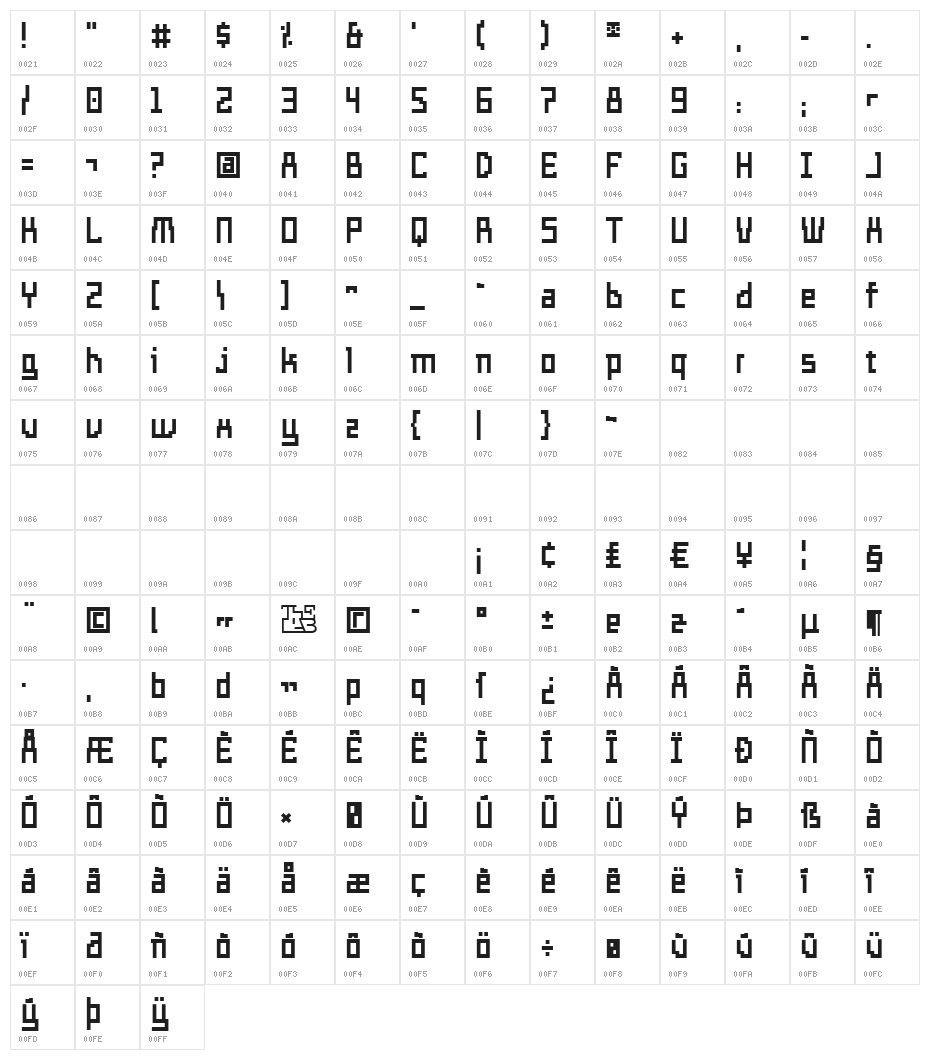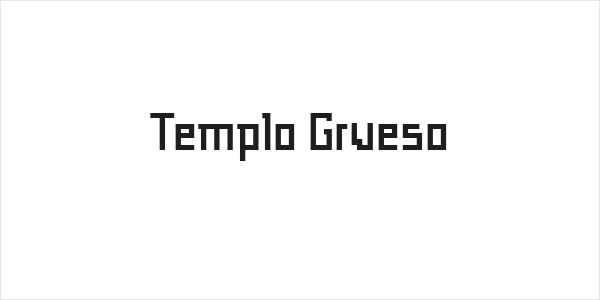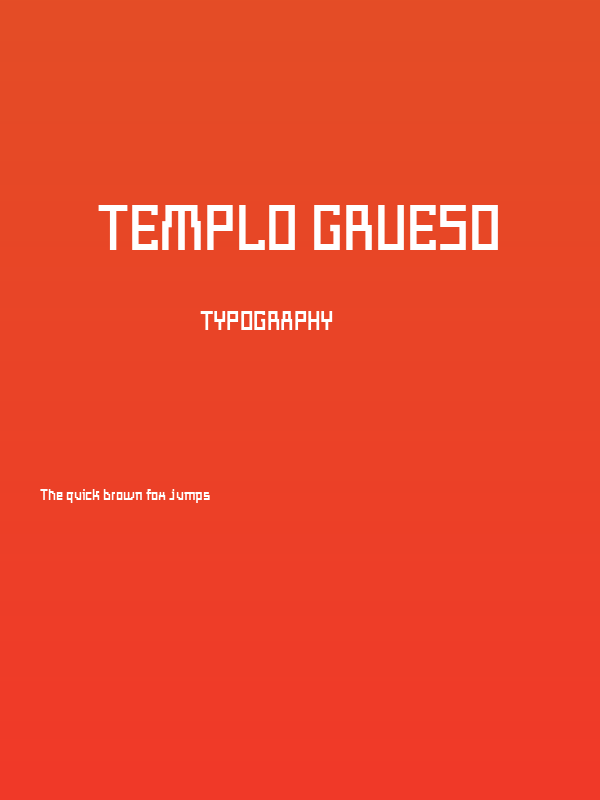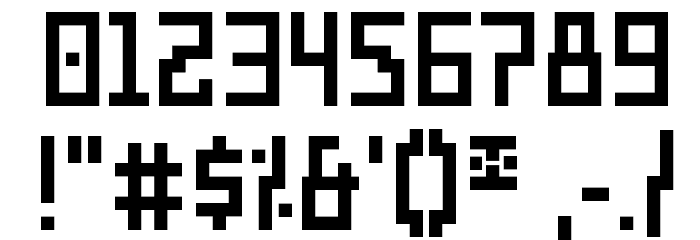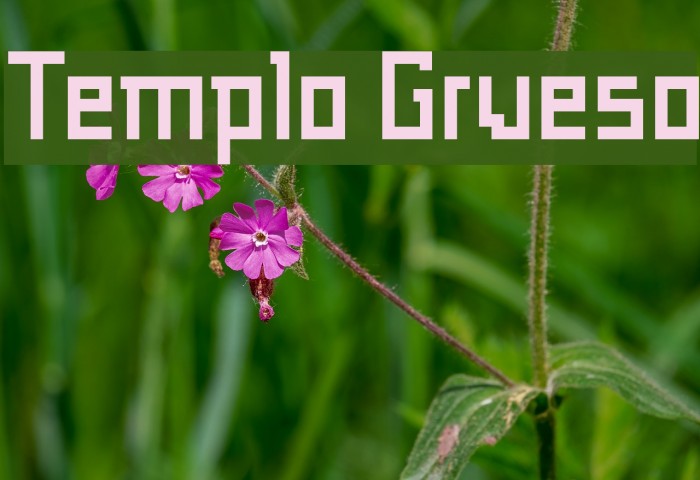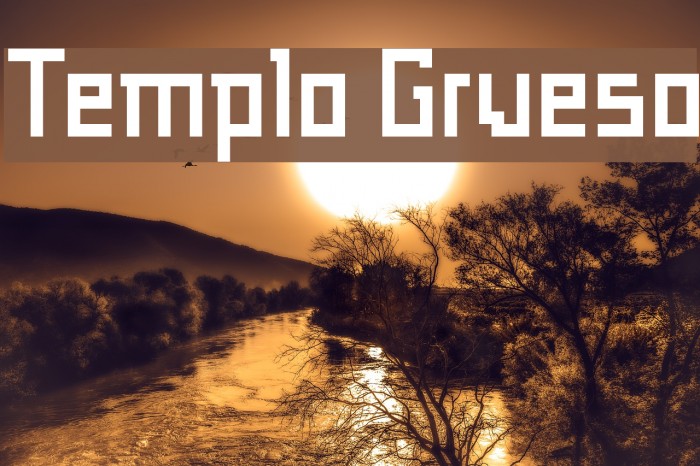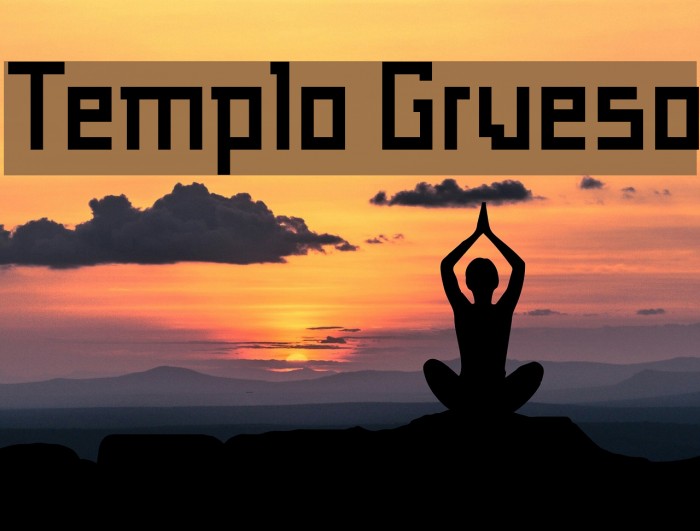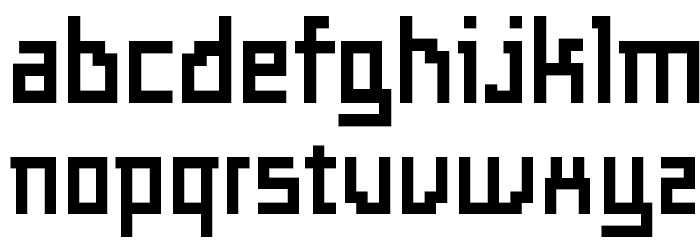
Templo Grueso Font
| Anwendungsfall | Logos, Headlines, Posters |
| Vorgeschlagene Projekte | Ideal for video game design, tech-themed posters, digital art projects, and retro-style branding. |